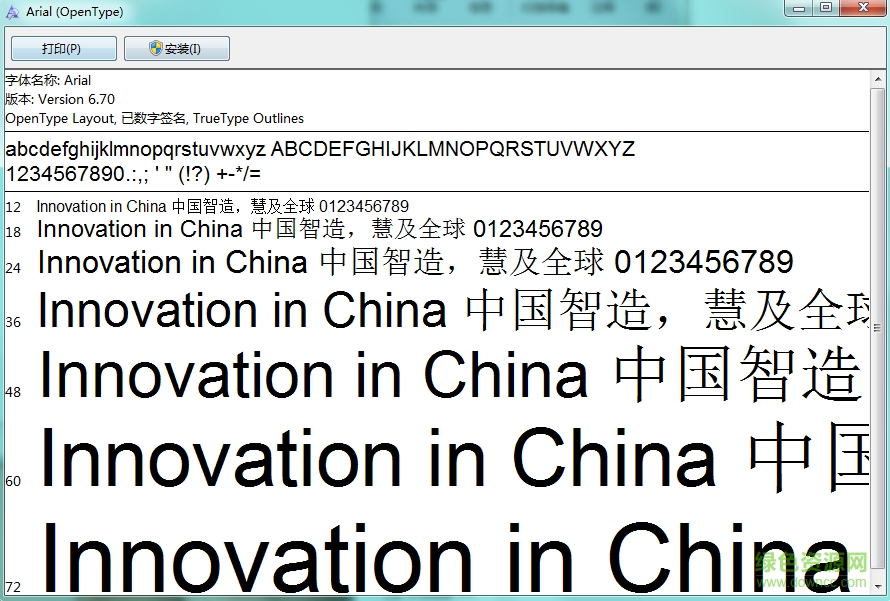
arial arabic字體是一款字形端正簡介、結(jié)構(gòu)清晰得體的一般公文習(xí)題,在高級(jí)office版本中常見,是arial系列的常規(guī)字體,很多網(wǎng)友在尋覓這款字體,綠色資源網(wǎng)今日為大家免費(fèi)分享!
Arial(Arabic)-Normal本身就是Arial,由于文件版本問題,高版本CD做的便顯示為前者,存的低版本的CDR的便顯示后者。